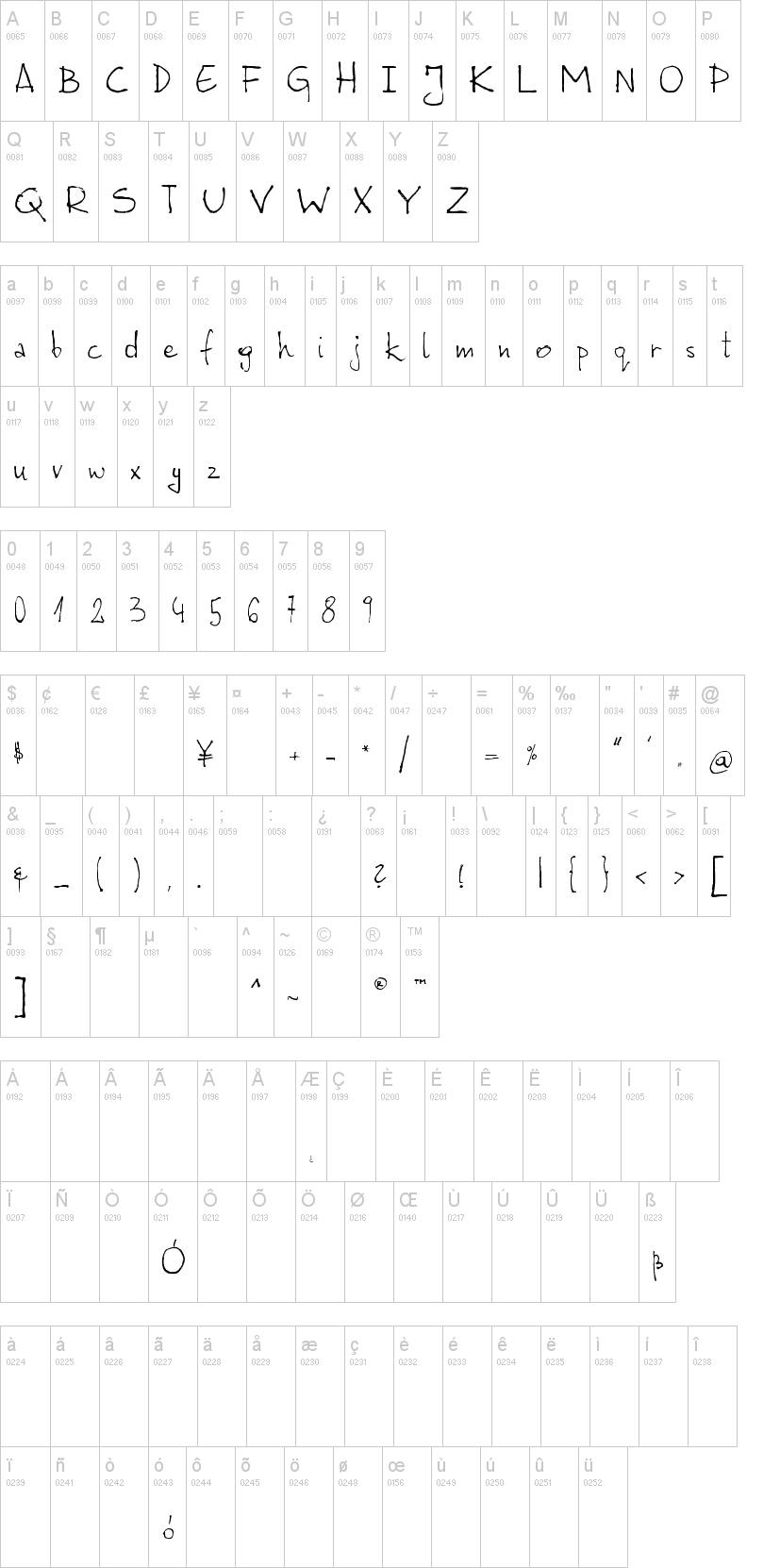
Hajduczek 是一款源自波兰的现代字体,由设计师 Maciej Hajduczek 创作。它具有清新、现代、活泼的特点,适合用于不同类型的设计项目,比如:海报、标识、标题、品牌标识等。它的字形设计具有良好的可读性,并且具有较强的视觉冲击力,可以让您的设计更加醒目。内容介绍
Hajduczek是一款非常不错的手写艺术字体,具有很好的视觉感,适合于文化类的宣传设计、商业类品牌的广告和产品包装设计以及个性化文字排版等较多场景。